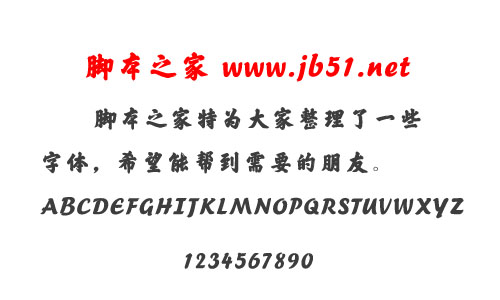
方正榜書行簡體字體(FZBangShuXingS-R-GB.ttf)是一款由方正字庫推出的手寫風(fēng)格的中文藝術(shù)字體,該字體字形瀟灑大方,醒目流暢,整體效果非常不錯,可以應(yīng)用于廣告設(shè)計、包裝印刷、產(chǎn)品設(shè)計、海報設(shè)計等方面,歡迎有需要的朋友們前來下載使用。